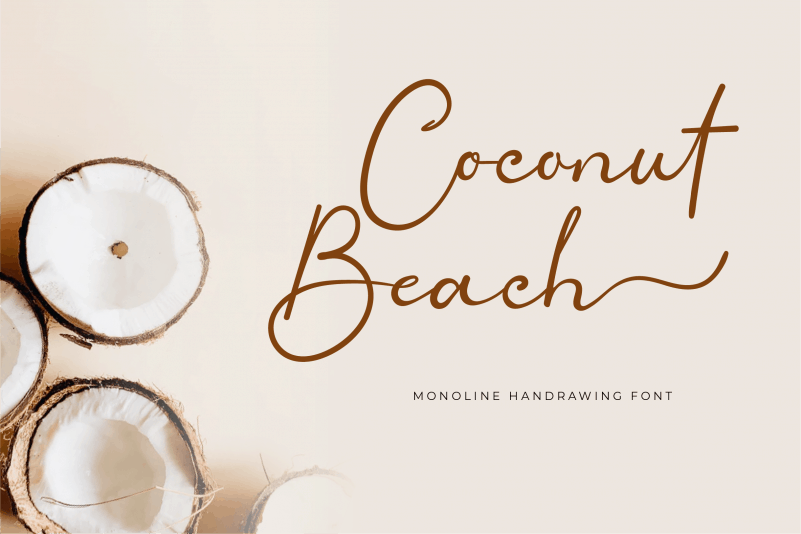
Coconut Beach Calligraphy Font – Download Grátis
A Coconut Beach Calligraphy Font é uma criação meticulosa que traz elegância com leveza para seus projetos digitais. Este belo mix entre elegância eterna e autêntica calligrafia oferece um estilo clássico, mantendo ao mesmo tempo uma presença amigável. Ideal para quem busca criar designs únicos e de alto nível, esta fonte é perfeita para aqueles que desejam dar vida à sua criatividade em um ambiente de praia tropical inspirado. Seja você um designer de sites ou um artista digital, Coconut Beach Calligraphy Font trará uma atmosfera descontraída e sofisticada ao seu trabalho, tornando a criação de designs singulares uma experiência agradável e eficaz.